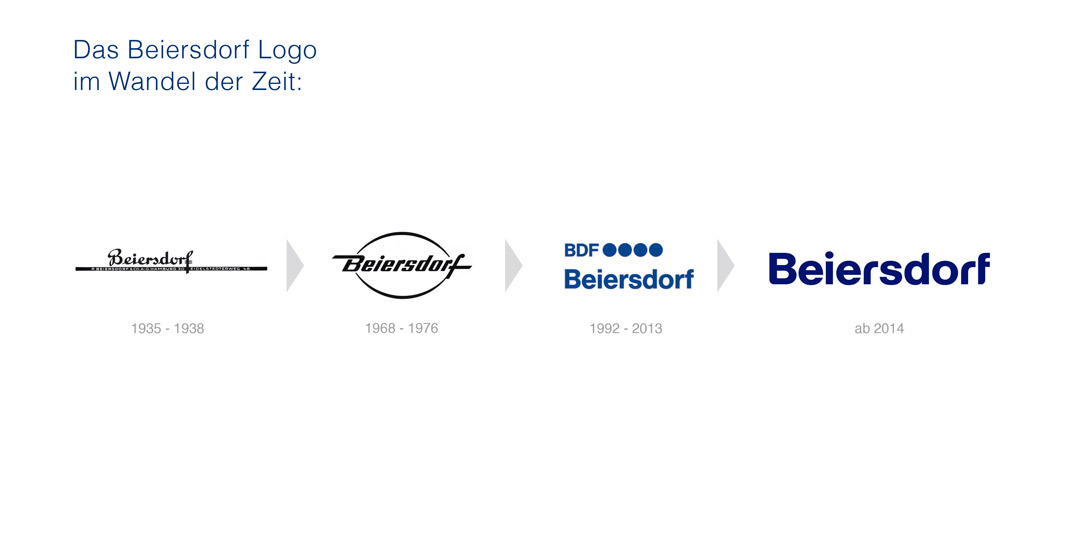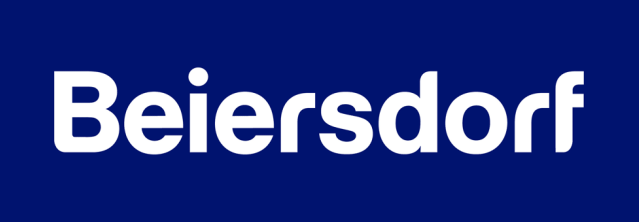
Oh … Beiersdorf!
Ich habe gerade im dt gesehen, dass Beiersdorf seine Wortmarke überarbeitet hat
Hmmm, gewöhnungsbedürftig! Der Schriftzug hat jetzt so eine Labello-Anmutung. Das r geht von der Form her noch, auch wenn solche reduzierten, abgerundeten Elemente als Formensprache eigentlich schon wieder durch sind. Beim B habe ich das Gefühl, dass die Abrundung der linken unteren Ecke einen etwas größeren Radius bräuchte, die Stelle wirkt auf mich zu dick. Und das f sieht nicht sehr standfest aus, das macht mich irgendwie nervös. Insgesamt hat der Schriftzug seine klassische Zeitlosigkeit verloren.
PS: Ich habe gerade noch mal das Labello-Logo zum Vergleich angehängt. Auffällig bei diesem ist, dass es inzwischen silberne Balken bekommen hat. Das erinnert stark an die grafische Gestaltung der Nivea-Visage-Produkte aus früheren Jahren.
Ob das daran liegt, dass da so mancher Gestalter des des englischen nicht soo fähig ist, und auf den Wunsch der Geschäftsleitung "Wir brauchen jetzt aber ein cutting-edge Logo!" (also ein Logo auf neuestem Stand) dann sich fragt: "Hmm cutting edge? Ecken schneiden?" und dann das aus der Schreibtischlade holt:
Ich hätte an Beiersdorfs Stelle einen der blauen Kreise beibehalten. Die vier Kreise im vorherigen Logo symbolisierten ja die vier Produktgruppen, die Beiersdorf hatte, als das Logo entworfen wurde. Jetzt sind es nur noch zwei, und nun hat man ganz auf die Kreise verzichtet. Für mich wäre es konsequent gewesen, von vier auf einen Kreis zu reduzieren. Das wäre eine nette Parallele zum Nivea-Kreis und würde außerdem sagen, dass sie sich stärker fokussiert haben. Und aus Gründen der Tradition wäre es auch passend.
:nicken: Das erinnert mich daran, dass es irgendwo mal eine Website gab, auf der jemand die angenommene Weiterentwicklung bekannter Logos gezeigt hat, basierend auf deren Entwicklungen in der Vergangenheit. War da auch Beiersdorf dabei? Man fragt sich beim Betrachten der Logoreihe in Deinem Beitrag in der Tat: Wie sähe der nächste Schritt aus? Hm, vielleicht sw …  :-?
Den Gedanken hatte ich auch, mit der Schlussfolgerung: aha! Jetzt ist die Punktreihe also wieder »frei«. ;-)
Außerdem grüble ich die ganze Zeit, bei welchem Logo dieser Schriftstil letztens auch zur Anwendung kam. Ich meine da gab es noch einen Kandidaten, der noch nicht in Martins verlinkter Liste steht. Oder ist das nich’ sogar ’ne Schrift?
Hab’s. Es war Schlagwerk und die Schrift hieß Harabara.
Gesundheit. Sieht ja gruslig aus.
So ist es! Und trotzdem fällt ein Unternehmen mit hochwertig verarbeiteten Musikinstrumenten »Made in Germany« drauf rein. *schluck*
Und Beiersdorf sieht jetzt auch eher aus wie ein »Gummimännl-Versand«. Auch wenn die Schriftzeichen dort sauberer stehen.
Ich assoziiere mit »Harabara« das gleichlautende japanische Wort, was wörtlich »Bauch-Bauch« bedeutet und das vor Aufregung schlagende Herz (das im Bauch verortet ist) meint. Ob das derjenige auch im Sinn hatte, als er diese Schrift »generiert« hat? :tutor:
Ja, Harabara wurde auch im dt gleich als Assoziation erwähnt.
*Lach* Ich kam drauf, als mich vorhin die Rhythmus-Muse küsste. ;-)
Interessant! Dann scheint man sich bei Schlagwerk zumindest inhaltlich über die Schriftwahl Gedanken gemacht zu haben. *mal was Positives unterstell*
dann müssten die comic-verlage die comic sans nutzen  :rockon: